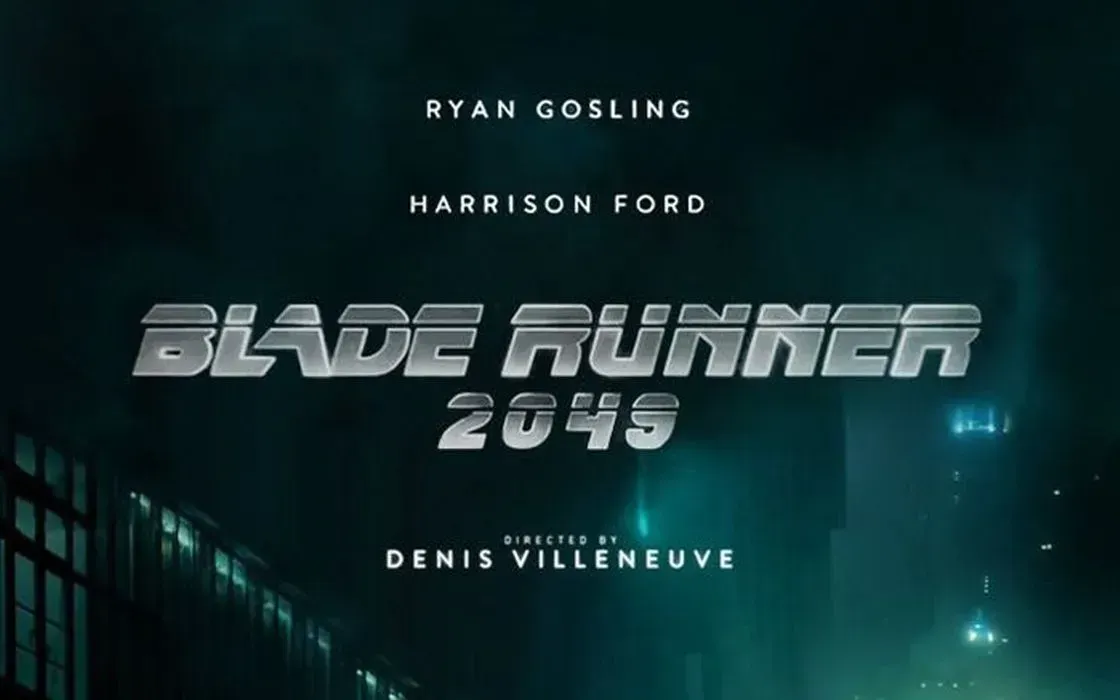
Font chữ SVN Blade Runner – Cứng cáp, Tương lai & Việt hóa đầy đủ
SVN Blade Runner là một kiểu font chữ sans-serif (không chân) mang phong cách khoa học viễn tưởng, góc cạnh và đậm chất tương lai. Lấy cảm hứng từ bộ phim điện ảnh huyền thoại Blade Runner, font sở hữu thiết kế nghiêng dứt khoát, các nét chữ vuông vức, chắc khỏe và mang hiệu ứng chuyển động, gợi cảm giác công nghệ cao, tốc độ và thế giới cyberpunk.
Đặc điểm nổi bật của SVN Blade Runner:
– Chữ nghiêng mạnh về bên phải, tạo hiệu ứng chuyển động, rất phù hợp cho tiêu đề, logo, poster hành động.
– Đường nét cứng cáp, sắc gọn, phù hợp với thế giới game, công nghệ, eSport, hoặc branding kỹ thuật số.
– Tạo cảm giác mạnh mẽ, bí ẩn và đậm chất tương lai, giúp thiết kế trở nên khác biệt và ấn tượng.
Font gốc Blade Runner Movie Font là một thiết kế không chính thức, được mô phỏng theo tiêu đề phim Blade Runner (1982) – một tác phẩm kinh điển thuộc thể loại khoa học viễn tưởng hậu tận thế. Font từ lâu đã trở thành biểu tượng trong văn hóa thị giác nhờ tính cách mạng về thẩm mỹ tương lai và chất cyberpunk.
Bản Việt hóa bởi nhóm SVN Fonts đã được xử lý cẩn thận, bổ sung đầy đủ dấu tiếng Việt, đồng thời giữ nguyên tinh thần cứng cáp và cấu trúc góc cạnh của bản gốc. Font hoạt động tốt trên các phần mềm như Photoshop, Illustrator, Canva, After Effects...
Nếu bạn đang tìm một font chữ cứng cáp, đậm chất công nghệ và đầy khí chất điện ảnh, thì SVN Blade Runner là lựa chọn lý tưởng cho các dự án thiết kế mang hơi hướng tương lai, hành động và viễn tưởng, từ game cho đến poster hoặc nhận diện thương hiệu mạnh mẽ.